新聞広告に「書体名」を掲載したのはなぜ!? ファミリーマートの新プライベートブランド「ファミマル」のパッケージデザインの舞台裏に迫る
新聞広告は時代を映す鏡…なんて言われますが、そこで使われているフォントも気になるモリサワnote編集部です。 2021 年10月19日朝刊に掲載された全面見開き(30段と言われます)広告に、社内がざわめきました。ファミリーマートの新しいプライベートブランド(PB)「ファミマル」をお披露目する内容です。
今回、その広告をきっかけに、パッケージデザインの舞台裏を追いかけてみることになりました!
1. A1ゴシックの名が広告に!?
冒頭の広告では「社内資料ですが、広告します。」とのコピーとともに、パッケージデザインのコンセプトやガイドラインが細かく紹介されています。よくよく見てみると、そこに「書体名:A1ゴシック」との言葉が書かれているではないですか!?
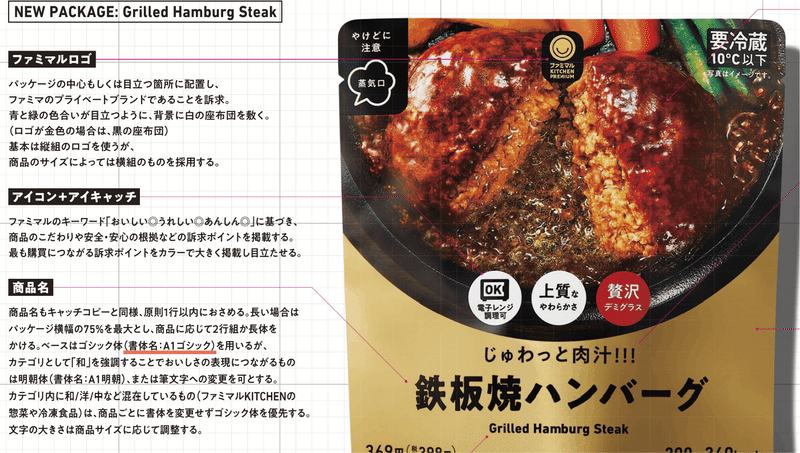
パッケージに使用する書体名を公表することは珍しく、SNS上でも注目する声が上がりました。ファミリーマートの社内資料が元になっているようです。
どういった意図で書体名を表記することになったのか、そしてそもそもどういう意図でA1ゴシックが選定されたのか知りたい!と思い、ファミリーマートに問い合わせました。
すると、この広告やパッケージデザインを手掛けた「The Breakthrough Company GO」のご担当者をご紹介いただき、お会いすることができました。ファミリーマートの新しいPBに対する熱い思いとともに、パッケージデザインの開発にまつわる深いお話をお届けします。
2. 【インタビュー】 新PB「ファミマル」とA1ゴシック採用の背景
The Breakthrough Company GO
Head of Art 小川 貴之(おがわ たかゆき)さん(左)
Business Producer 田中 陽樹(たなか はるき)さん(右)
ー今日はよろしくお願いします。ファミリーマートの新PBを紹介する新聞広告は、インパクトがありましたね。
田中:ありがとうございます。伝えたかったのは「ファミマル」が家族にも安心してすすめられるファミリークオリティのブランドであることです。社内向け資料を用いたのは、あえてブランド開発の裏側を見せることで、製造過程から安心できるよい商品だと理解してほしかったから。実は、広告にはもう1つ、別のパターンがあって、競合PBのハンバーグとの消費者調査を示したものです。
田中:事前のイメージでは負けていたものの、実際に食べていただければ、おいしさでは負けていない。ファミリーマートでは、かなりの商品群で消費者から高い評価を得ています。それを世の中にも、ファミマの店舗で働く人にも伝えたかったのです。
ーファミリーマートには以前にもPBがありましたが、「ファミマル」ならではのコンセプトやパッケージを作る際に苦労されたポイントはありますか?
田中:ファミマルは、「おいしい◎うれしい◎あんしん◎」の二重丸(マル)品質をファミマと掛け合わせたブランド名称です。一つ一つの商品の特徴や良さを、お子様から高齢者まで誰にでもわかりやすい伝え方を目指しています。コンペで弊社が担当することが決まってから本格的に商品パッケージのデザインを進めているわけですが、総アイテム数は800以上に及びます。商品の価値をどう伝えていくべきか、ファミリーマートの各担当者とディスカッションしながら形づくっているところです。
ーなるほど。では改めてファミマルのパッケージデザインのコンセプトを聞かせてもらえますか。
小川:ファミマ(Famima)の考えるユニバーサルデザイン(Universal Design)という考え方から「F-universal」という言葉をデザインコンセプトに掲げました。冒頭の3文字にあるFunから、楽しさを作るという意味も込められています。店頭にファミマルの商品が置いてあることで、買い物が楽しくなればなと思っています。
ー実際、どんなことを意識されたのですか?
小川:シズル感あるビジュアルと、シンプルで直感的な言葉を用い「5秒でわかるパッケージ」を目標にしています。商品名やキャッチコピーは大きさを含め、徹底的に読みやすさに気を配りました。新聞広告にもあるようにパッケージデザインはフォントも指定しています。
ーユニバーサルがコンセプトとのことですが、商品名の指定フォントはA1ゴシックで、いわゆるUDフォントではないですよね。
小川:UDフォントは比較的小さな文字や文章での読みやすさを意識して使われることが多いのですが、商品名を大きく表記することで読みやすさ、ユニバーサルデザインを達成することを考えたため、UDフォントであることにはこだわりませんでした。それより、コンセプトに合致しているか、コンビニの商品にふさわしいか、など多岐から考えました。コンビニのPB商品は、紙コップやスポンジなどの日用品も含まれるほか、食品でも惣菜からお菓子など多種多様です。
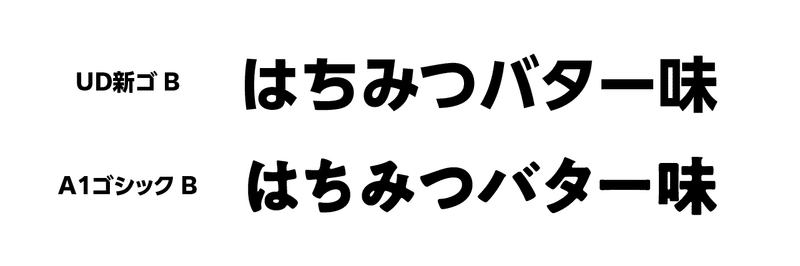
編集部作成
ーなるほど。 “ファミマルの” ユニバーサルデザインコンセプトに合致しているかどうかが重要なポイントだったんですね。
小川:そうなんです。UDフォントにこだわることより、楽しさとの両方を兼ね備え、多様なターゲットにもフィットし、あたたかく、おいしそうだと感じてもらえる性格のフォントを検証してきた結果として、A1ゴシックとフリーフォント系丸ゴシックの2つに候補を絞りました。
ー最終的には2択からA1ゴシックが選ばれたわけですね。
小川:そうですね、フォント自体に、キャラクターというか温かみのある性格を持ち合わせている点を評価しました。文字の角に丸みがあり、大きくした際にも読みやすい。ファミマルの顔とするうえでも、最終的には親しみやすさと書体のクオリティの高さでA1ゴシックに決めました。私たちが考えるユニバーサルデザインは達成できたと感じています。
ー基本となる書体やコンセプトが決まっている中で、個別に商品パッケージをデザインする際に気を配っていることはありますか?
小川:PBのパッケージデザインは、広告に記載したようにデザインのルールを決めるまでが重要だと思われますが、実際は個別の商品パッケージに適用させることが肝要なのです。ルールベースで進められるかなと甘く見ていた部分がありましたが、いざはじめてみると、パウチの存在や動かせないバーコード位置などパッケージや商品特性ごとのイレギュラーな要素がたくさんあることに気付かされました。
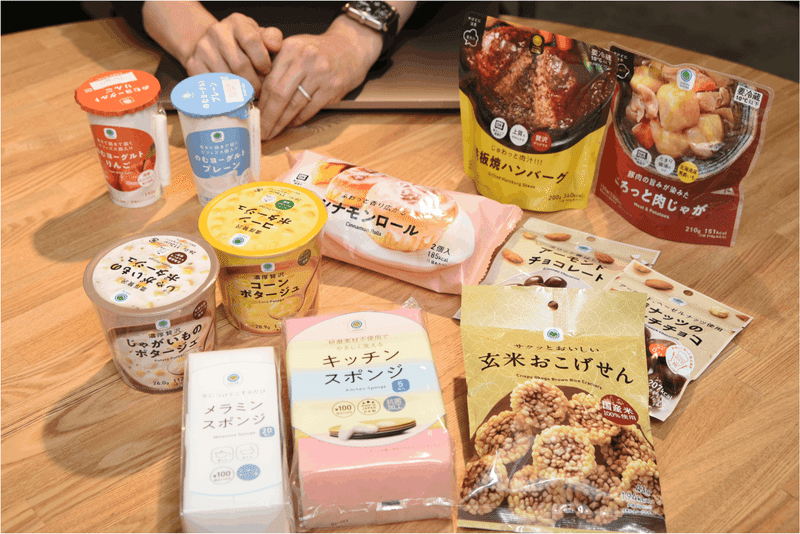
ールールを基に商品特性に合わせていく…なかなか、大変そうですね。
小川:飲むヨーグルト1つ取っても、いろんな味付けのものが並んだ際に個性が際立つ見映えを考えたデザインが求められます。一部が透明になった包材のおせんべいは、中身が入って棚に並んだ状態を意識して、細かな粉が目立たないようパッケージの下部分は不透明なデザインにするなど、固有の配慮が必要です。そもそも商品は三次元なので、平面的なグラフィックとは印象が異なることをイメージしないといけません。
ーパッケージデザインの標準に据えている商品はありますか?
小川:ファミマルのロゴやキャッチコピー、商品名のバランスはポテトチップスを基本にしています。ただ、このルールを米菓に適用すると、同じPBであるとは見えますが和風らしさが削がれてしまう。その際には「A1明朝」を用いることにしています。おつまみの場合は、それでも不十分でかつ縦型のパッケージが多いことから、縦書きでの筆文字にして独特のシズルを表現しています。
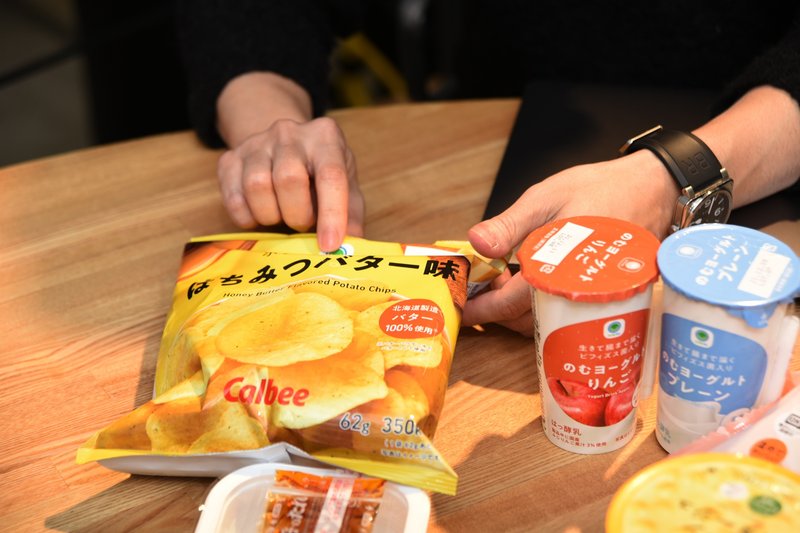
ー商品によってはフォントも変えて、同じPBの中でもデザインの差別化を図るんですね。
小川:その通りです。例えば同じナッツでも、おつまみと低糖質食品では購買者が異なるので陳列も別の棚に変えるべきで、デザインで明確に区別する必要があります。PBとしての統一感を図りながら、商品のよさを最大限引き出すパッケージが大切で、フォントを含めてデザインにはやはり神経を使います。
ー店頭での陳列を意識したデザインにするということですね。
小川:他のコンビニを含め、店頭に足を運んで陳列を研究しました。店舗の規模や商圏によって商品内容は異なり、什器を含め陳列はだいぶ違います。チルドや冷凍品、日用品、お菓子、おつまみなどコーナーごとにデザインや基調を変えて、その中でファミマルの商品の個性が伝われば、消費者のコンビニ体験のストレスが減らせると思っています。加えて、店内で働くスタッフは外国人の方も多く、デザインの違いでカテゴリーが判れば品出しで混乱することなく済むでしょう。
ー奥が深い世界ですね。店舗や消費者からの反応はいかがですか?
田中:おかげさまで広告でも用いた「鉄板焼ハンバーグ」は、旧商品比約150%の売上と聞いています。女性に人気の冷凍スイーツシリーズのフォンダンショコラも好調で話題になりました。消費者を意識したパッケージは書体にも助けられている部分があるなと感じています。
ーありがとうございます。今後の商品展開も楽しみですね。
田中:今後ほかのカテゴリもファミマルで展開できるか検討されています。ファミリーマートでは現在の売上比率で30%のPBを、2024年末に35%以上にすることを目指しています。また、現在はこれまでの商品(ファミリーマートコレクション・お母さん食堂)と混在している状況で、少しずつファミマル商品を拡大させている段階です。これも従来商品から新商品への展開を急がず、廃棄を極力少なくするための展開です。正直さや誠実さが愛されるブランドとして広まっていけばうれしいです。
3. 取材を終えて
コンビニの店頭で何気なく目にする商品にも、その魅力を最大限引き出せるようなパッケージデザインの工夫がちりばめられているのがよく分かりました。ましてやPBはコンビニ各社が特に力を注ぐ商品たち。デザインのこだわりもひとしおです。
デザインのルールを定めるだけではなく、商品の個性それぞれに適合させていく重要性が伝わってきたのではないでしょうか。
モリサワとしては、ブランドイメージを作っていく上で、コンセプトにあったフォント選びがいかに重要であるかを改めて感じるインタビューでした。
皆さんもファミリーマートに足を運んだ際はぜひ、ファミマルのデザインに秘められた工夫に思いを巡らせてみてはいかがでしょうか。(担当:Y)